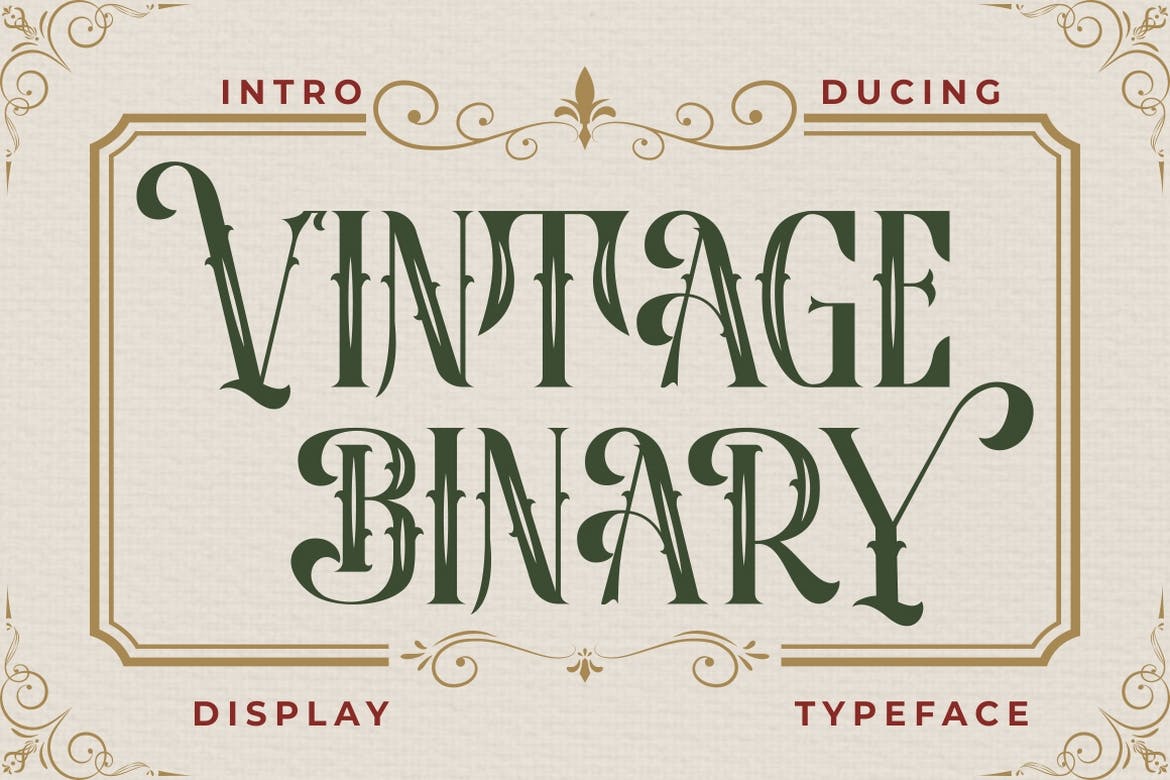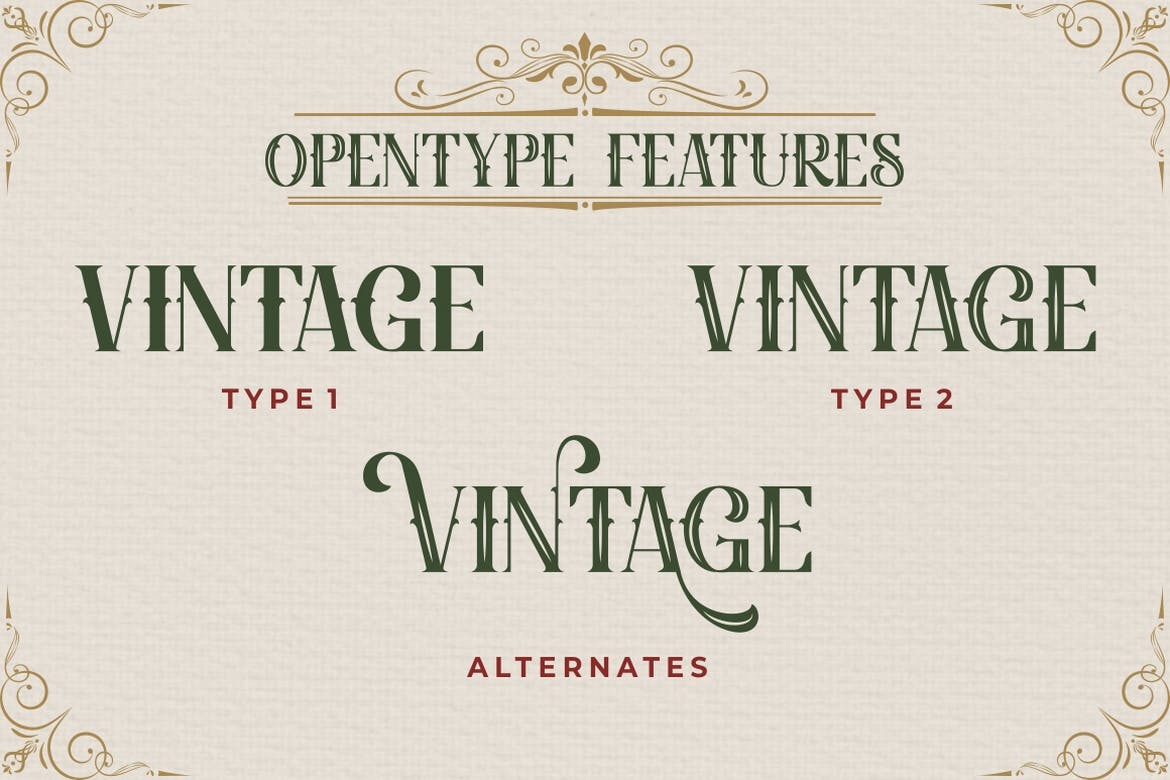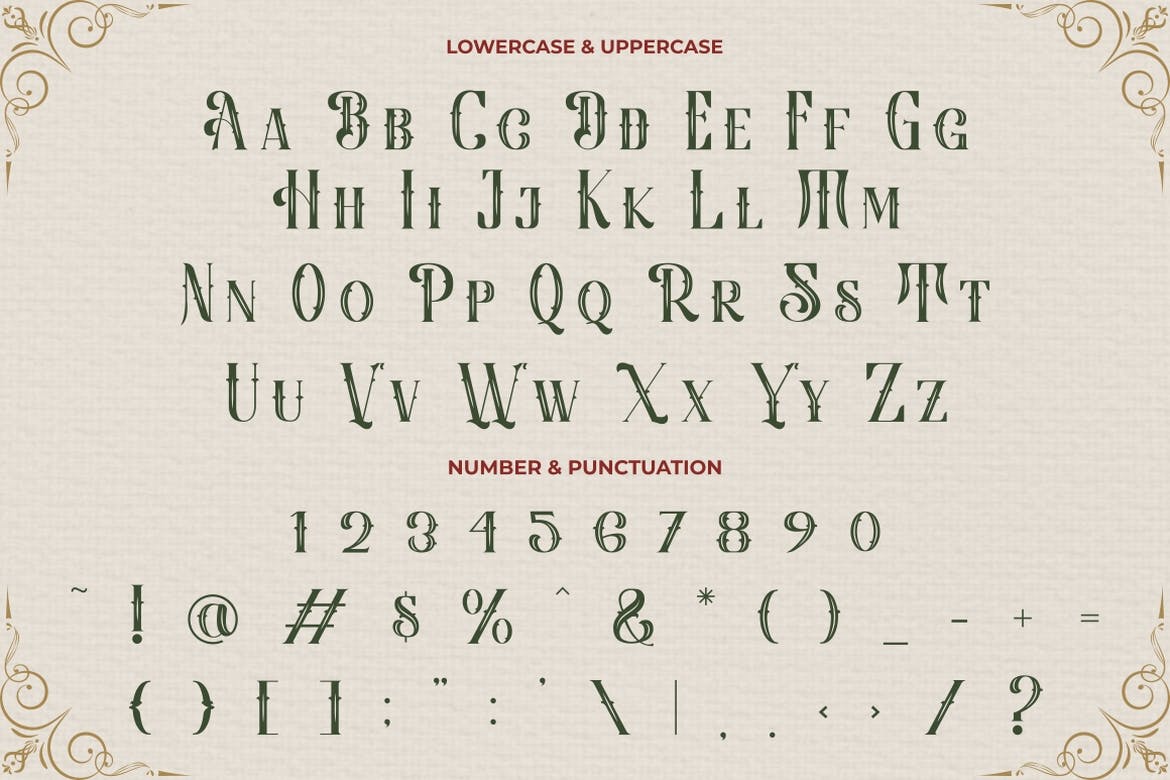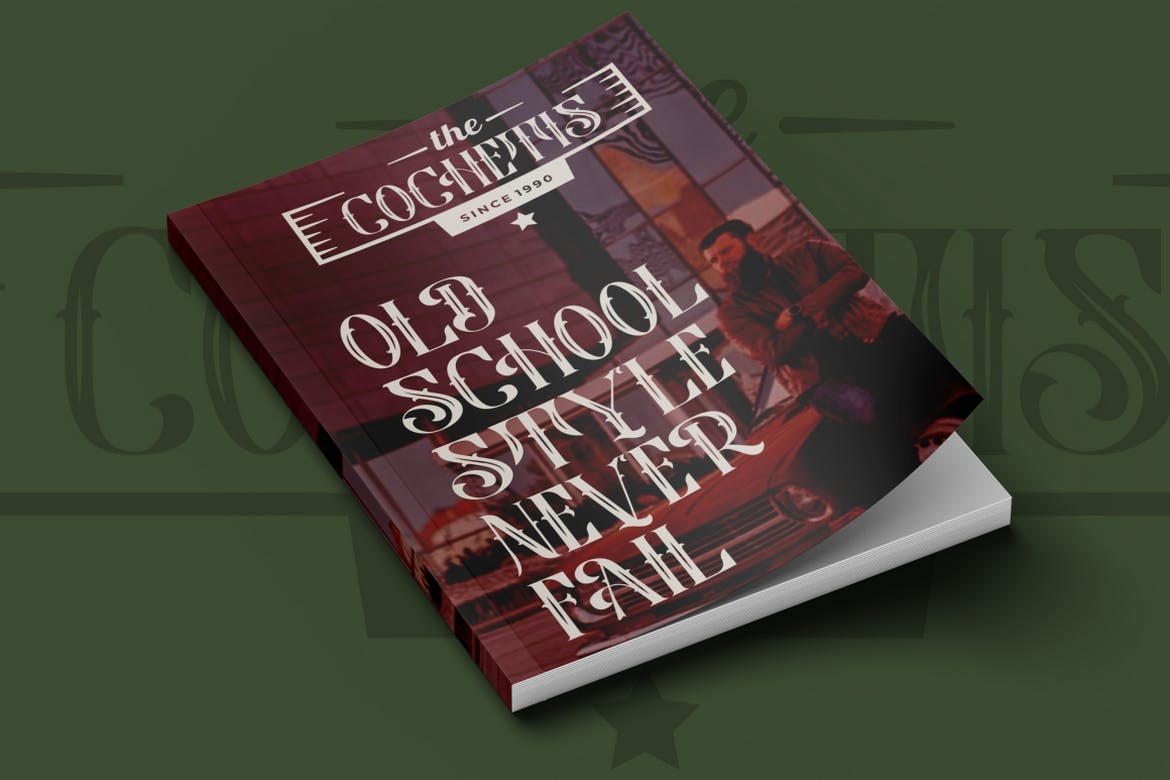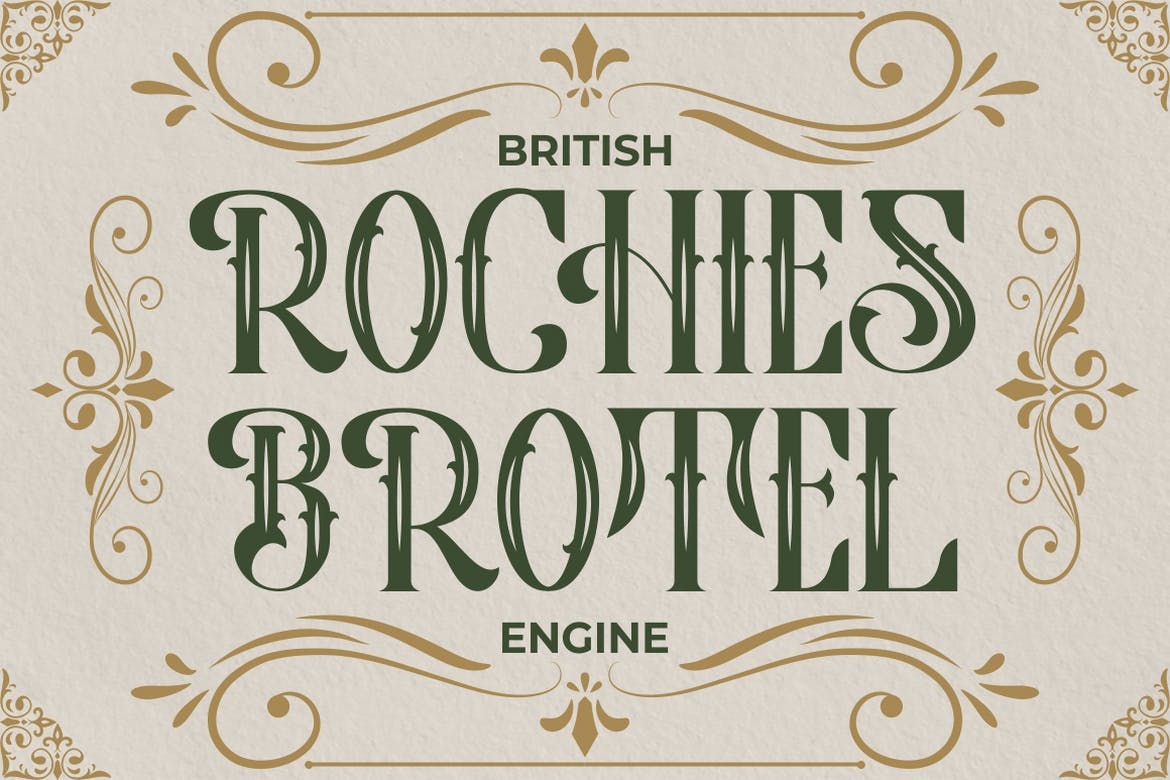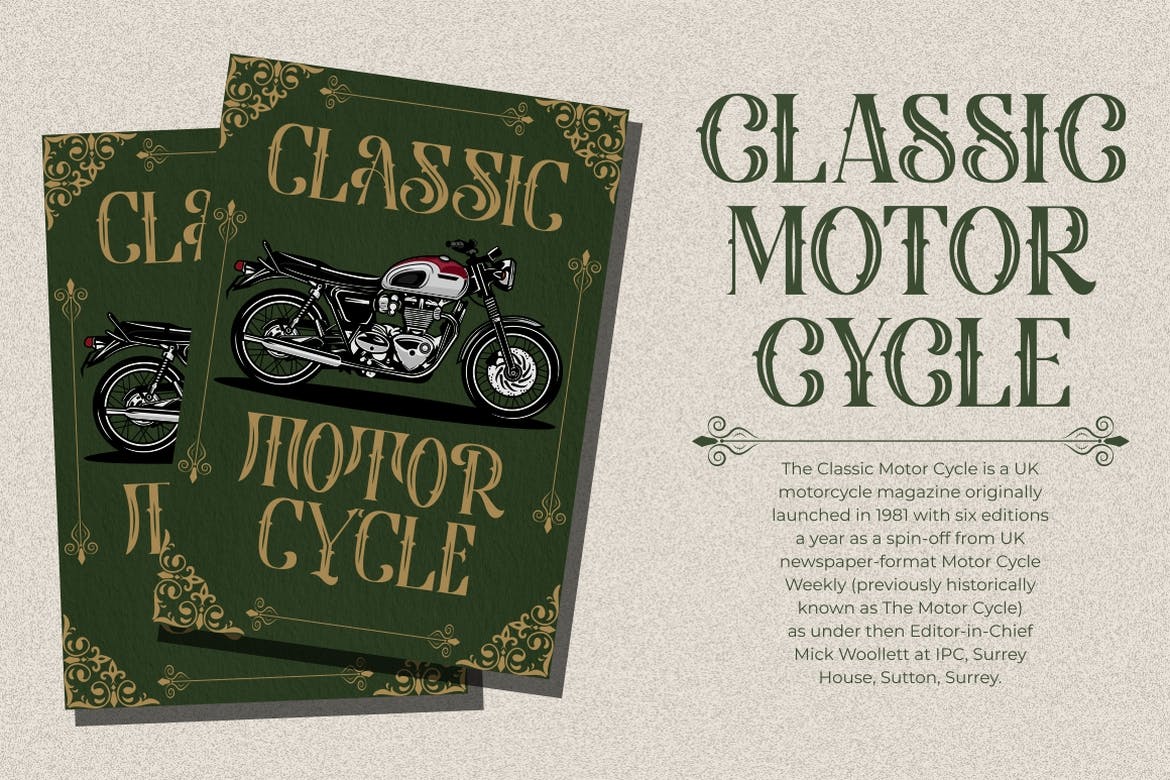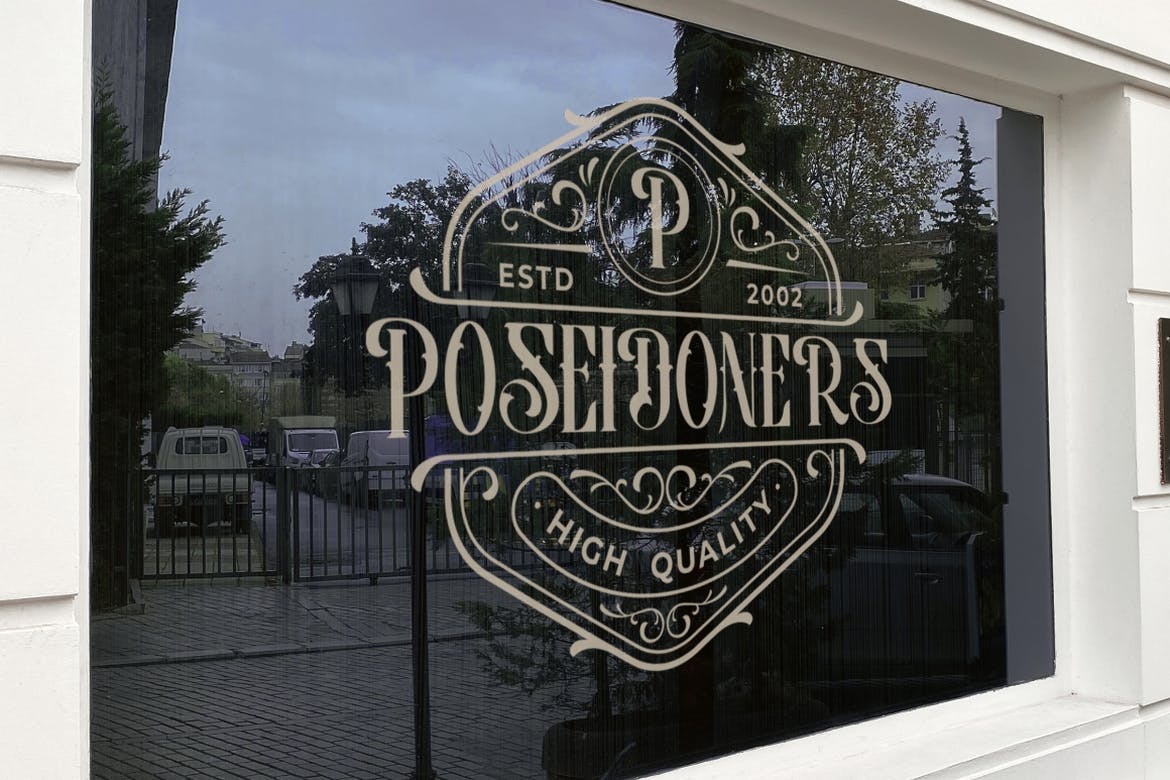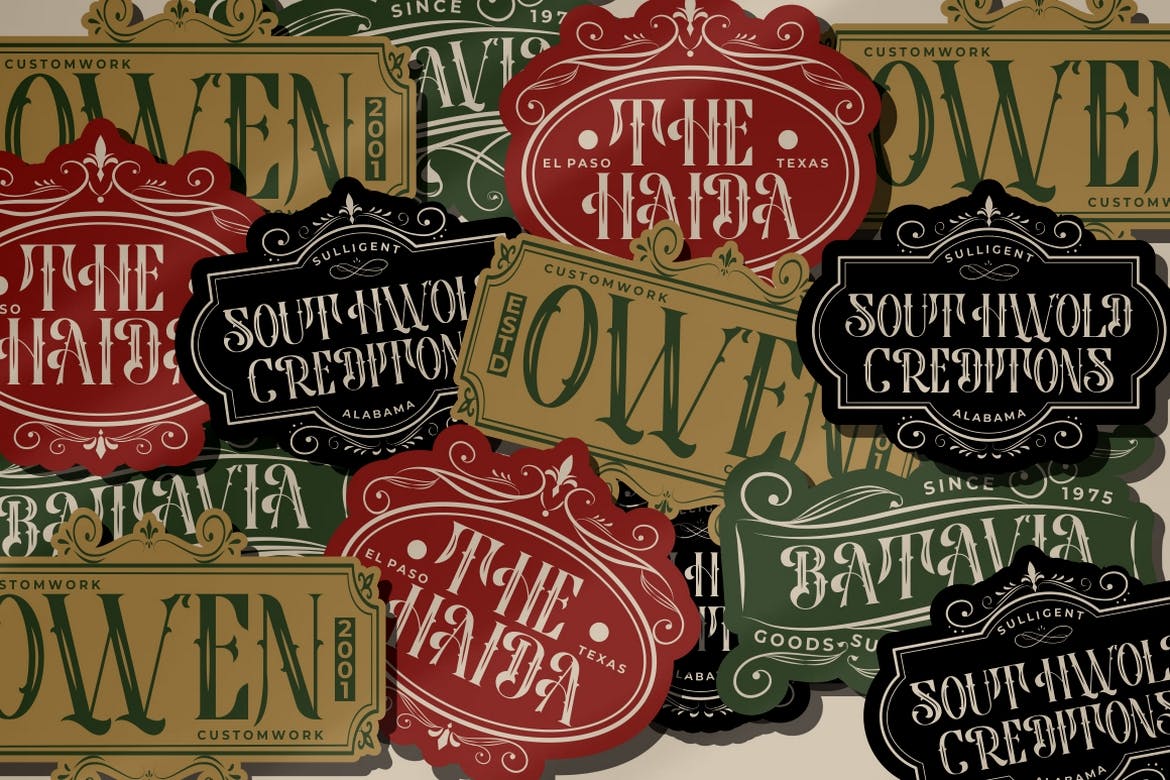
فونت نمایشی وینتج باینری
فونت نمایشی وینتج باینری، یک فونت جذاب است که جوهره زیباییشناسی وینتج و رترو را در خود دارد. با سبک نمایشی کلاسیک خود، احساس نوستالژی را القا کرده و به طراحیهای شما جذابیت و زینت خاصی میبخشد. این فونت گزینهای مناسب برای لوگوها، نشانها، امبدها، عناوین، تیترها، پوسترها، مواد برندینگ و موارد دیگر است.
سبک وینتج و رترو فونت وینتج باینری، جذابیت و نوستالژی دورانهای گذشته را زنده میکند. طراحی کلاسیک این فونت جوهره تایپوگرافی وینتج را به تصویر میکشد و جذابیت بیزمانی به طراحیهای شما میبخشد. این فونت با عناصر زینتی و تزیینی خود، لایهای اضافی از جذابیت بصری و خلاقیت هنری را به کارهای شما اضافه میکند. چه در حال طراحی لوگویی برای یک برند الهامگرفته از رترو باشید، چه برچسبی وینتج یا پوستر چشمنوازی بسازید، وینتج باینری فونتی چندمنظوره است که به شما در دستیابی به نتیجهای اصیل و بصری کمک خواهد کرد.
با فونت نمایشی وینتج باینری، میتوانید طرحهای خود را با جذابیت وینتج، حس رترو و جزئیات هنری پر کنید که توجهها را جلب کرده و تأثیری ماندگار بر جای میگذارد.